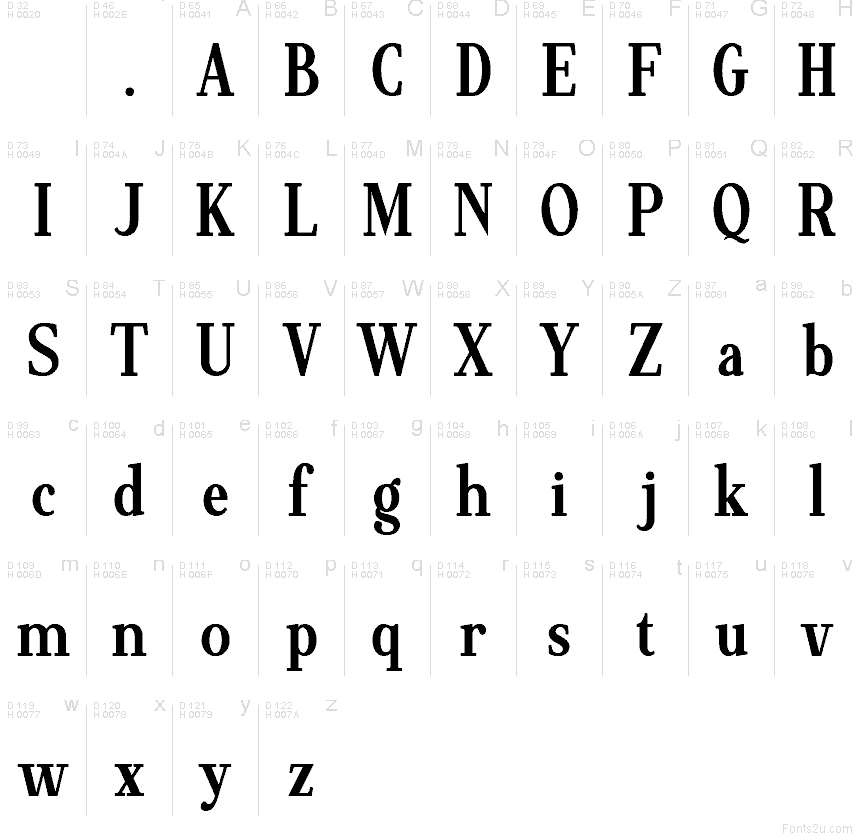
Minims Regular von Flawless & Co. ist eine kostenlose Serifenschrift mit einer markanten, traditionellen Ausstrahlung, die fast wie aus repetitiven, aufrechten Strichen konstruiert wirkt. Die Buchstaben setzen auf einen soliden vertikalen Rhythmus und kompakte, kantige Abschlussdetails. Das verleiht der Schrift eine leicht strenge Textur, die dennoch ruhig und literarisch wirkt.
Durch diese ausgewogene Farbwirkung eignet sie sich ideal für redaktionelle Magazine, Museums-Poster, Buchtitel, Etiketten oder kurze Brand-Headlines, bei denen das repetitive Strichmuster für sich selbst spricht. Da sie kostenlos verfügbar ist, macht sie sich auch hervorragend für Titel-Cards oder Initialen – besonders dann, wenn Sie eine Serifenschrift suchen, die reduziert, beständig und fast schon klösterlich anmutet.